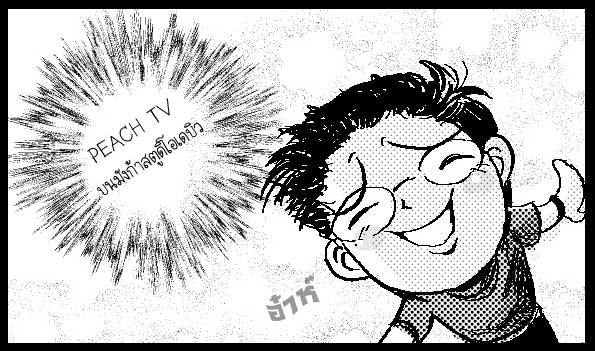
PeachTV
ส่วนเรื่องข้อความ
คือไม่รู้ว่าจะพิมพ์อะไรดี
เลยเข้าพันธุ์ทิพย์แล้วปรับเป็นฟอนต์เรา
ง่ายดี ไม่ต้องพิมพ์  :42:
ฮ้ายยยยย สวยอ่า ชอบๆๆ
น่ารักสุดจัยขาดิ้นอ่า กรี๊ดดดดดดด
ขนาดภาษาวิบัติแมนยังชมเลยนะเนี่ย :12:
แต่ตัวนี้สวยเรียบร้อยน่าอ่านมากเลยจ้ะ
อยู่ในงานป๋าแล้ว :42: